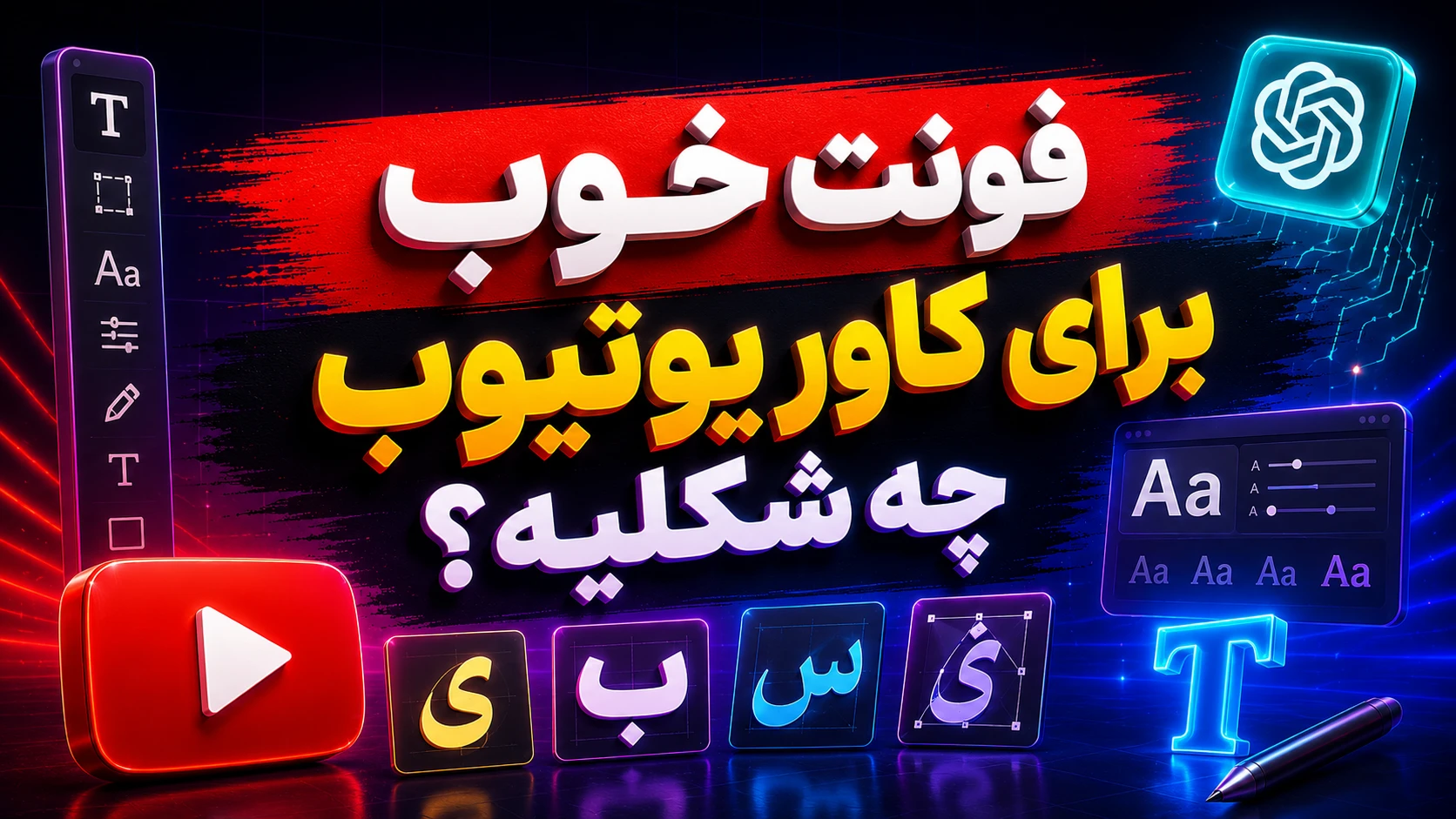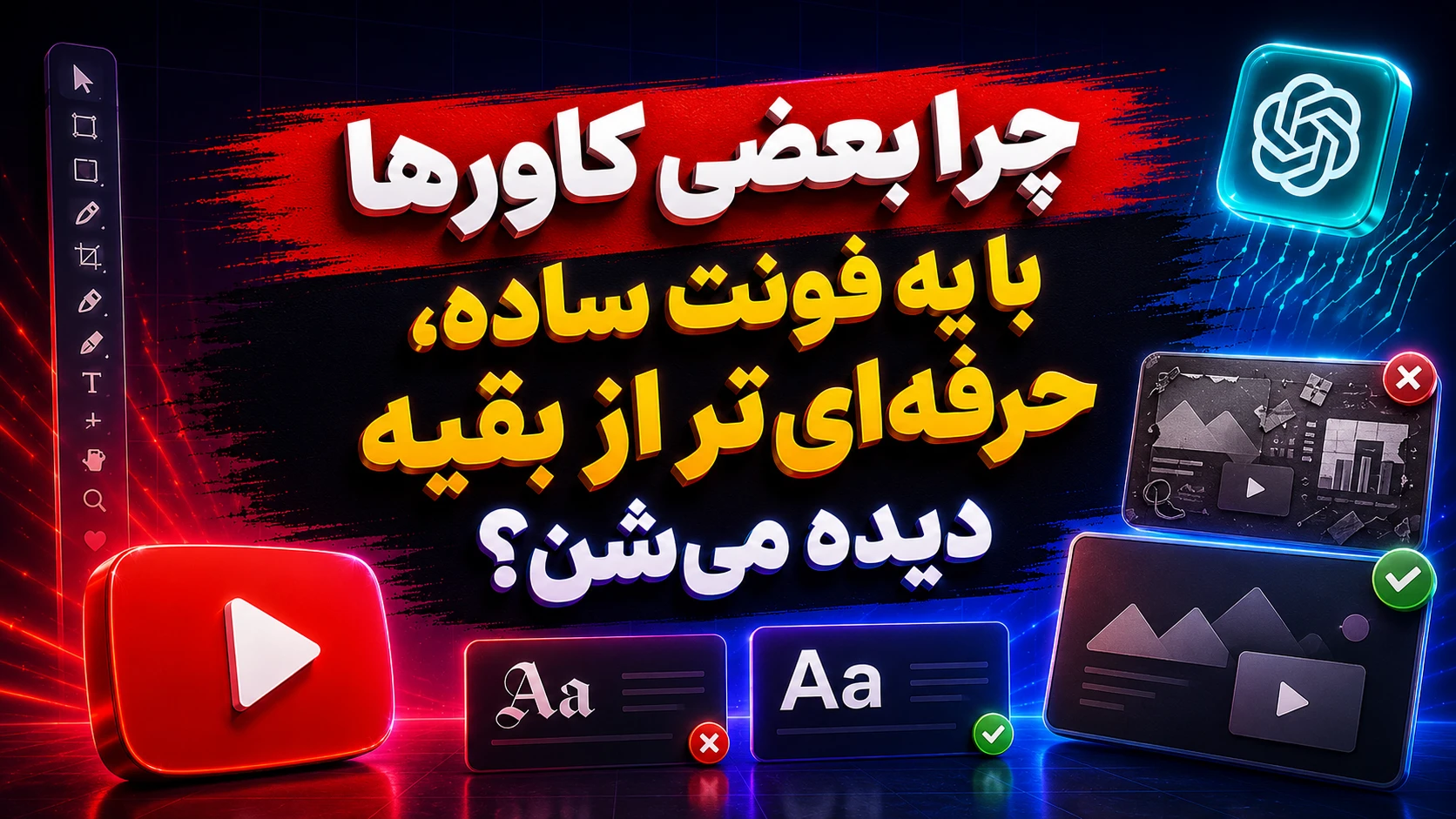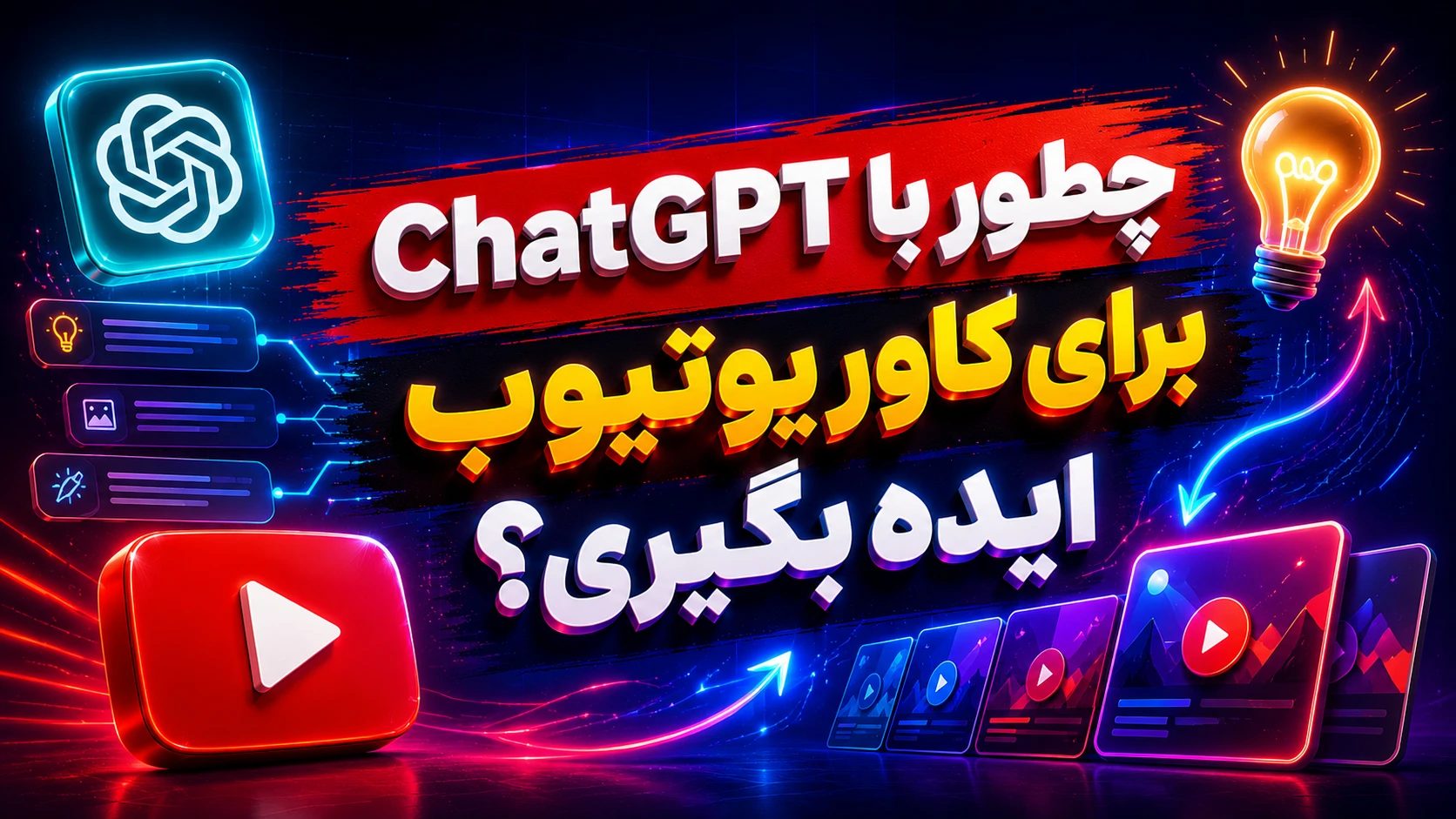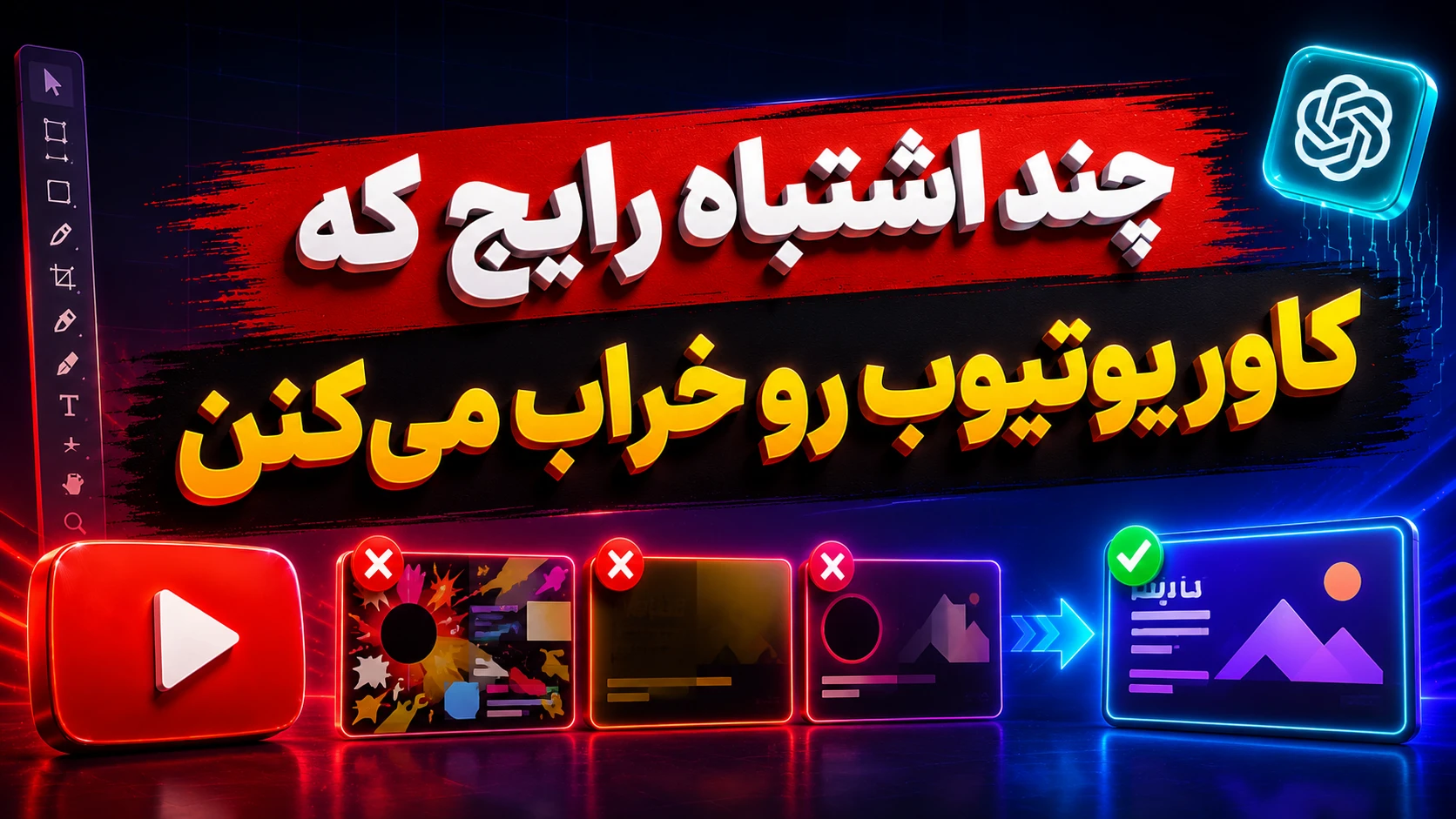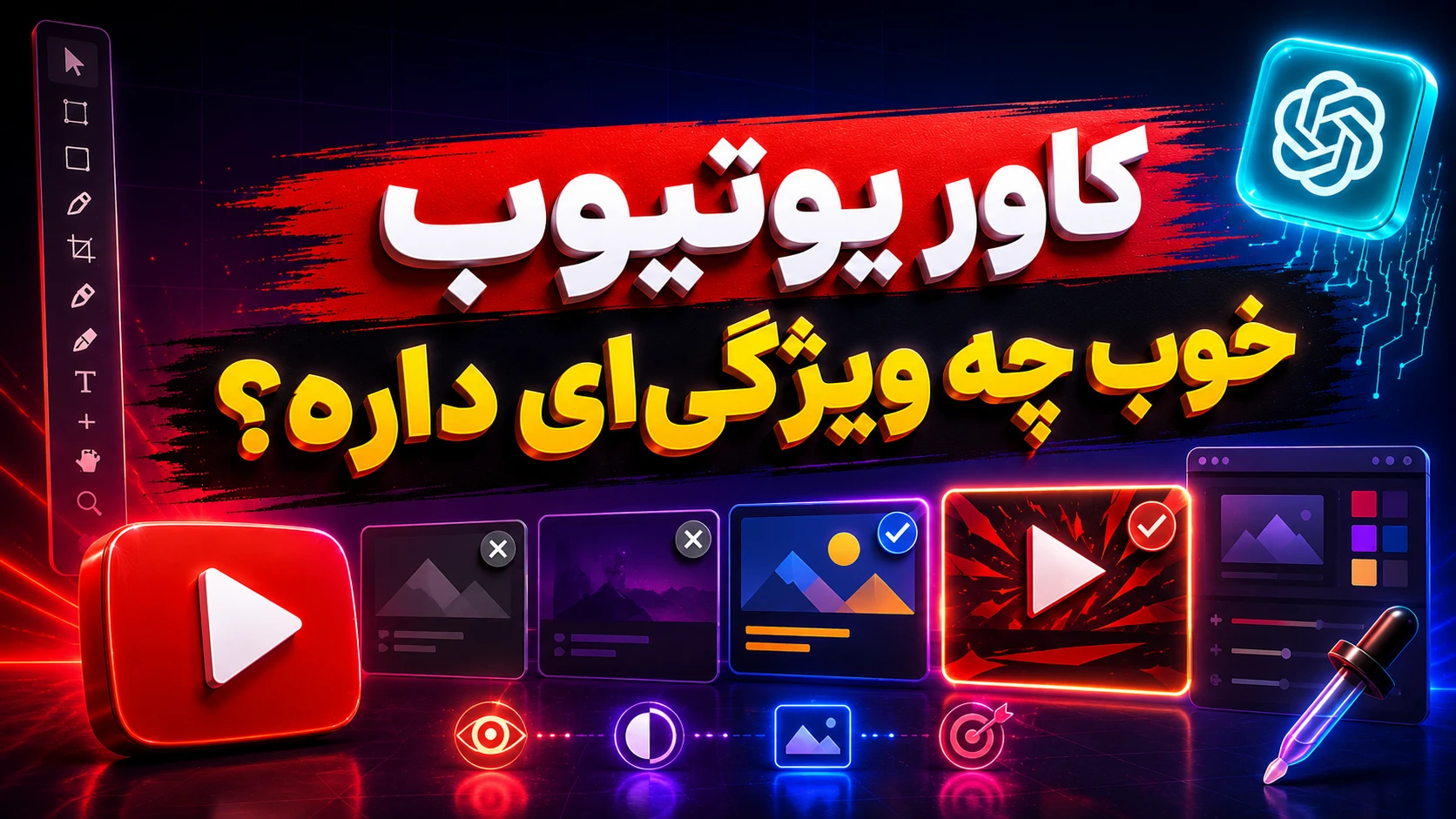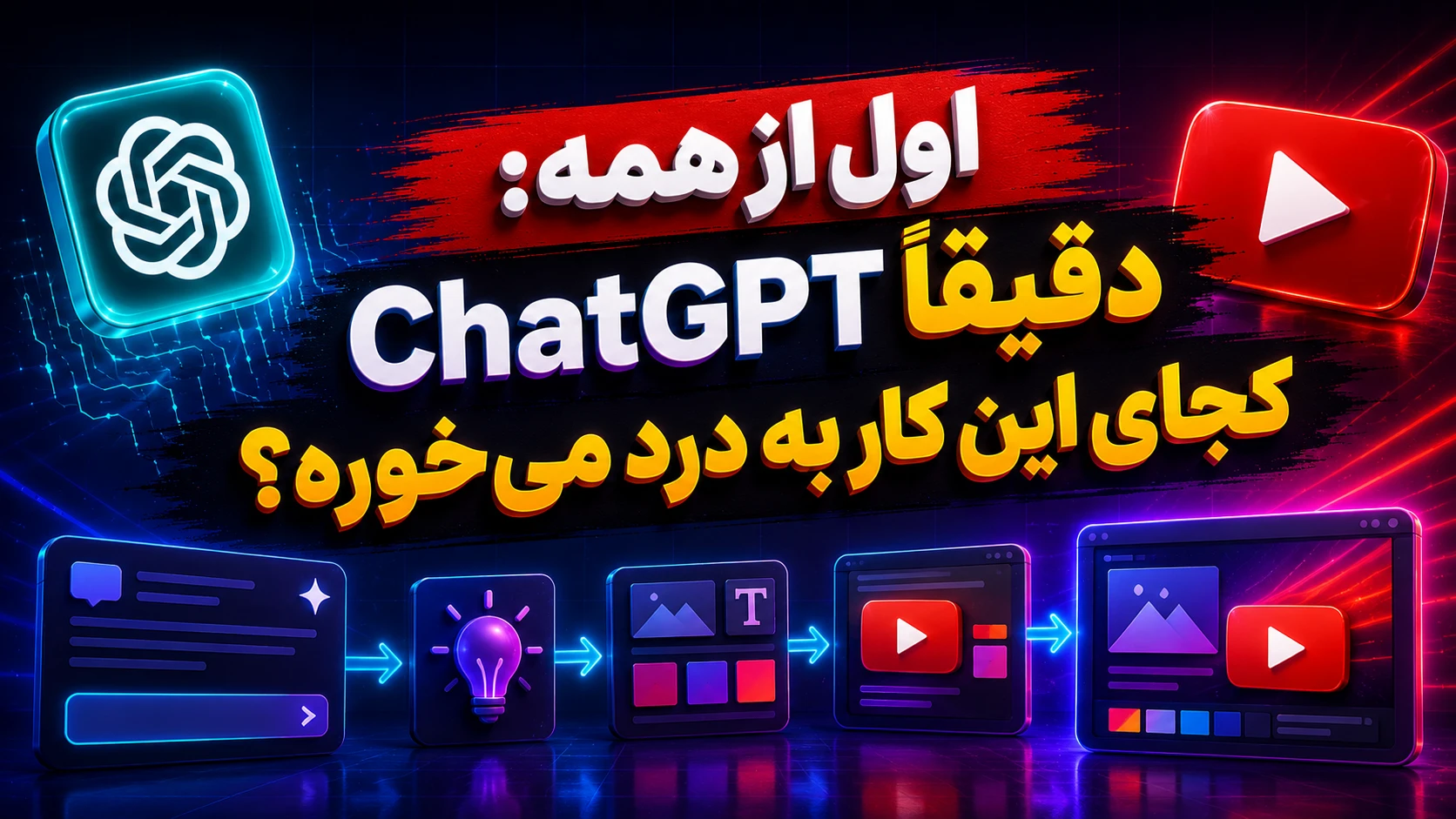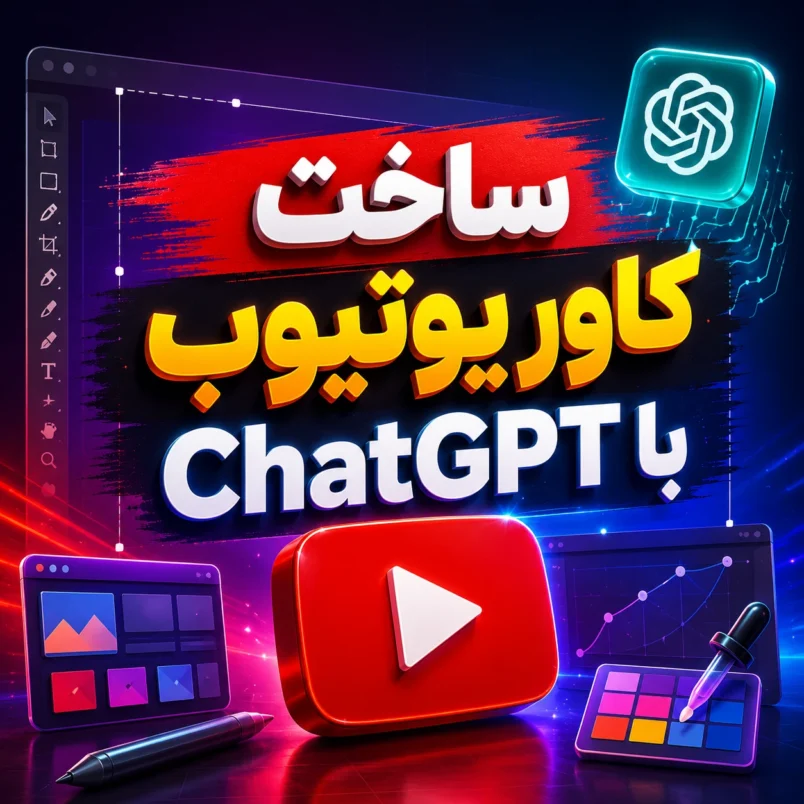
ساخت کاور یوتیوب با ChatGPT؛ این فونت‌ها ویدئوت رو نجات می‌دن!
ساخت کاور یوتیوب با ChatGPT
اگر بخوام خیلی ساده بگم، کاور یوتیوب همون چیزیه که یا کاربر رو نگه می‌داره، یا باعث می‌شه از کنارش رد بشه. یعنی قبل از اینکه خود ویدئو دیده بشه، قبل از اینکه عنوان باز بشه، قبل از اینکه کسی بفهمه اصلاً تو چی گفتی، کاور باید کار خودش رو بکنه. یوتیوب هم دقیقاً روی همین نقطه دست می‌ذاره؛ توی راهنمای رسمی خودش می‌گه بیننده‌ها معمولاً اول از همه thumbnail و title رو می‌بینن و همون‌ها بهشون کمک می‌کنن بفهمن ویدئو درباره چیه و تصمیم بگیرن که بازش کنن یا نه. یوتیوب همچنین پیشنهاد می‌کنه از تصویر شلوغ و پیچیده دوری کنی، متن اگر گذاشتی خوانا باشه، و thumbnail تا جای ممکن بزرگ طراحی بشه.
اول از همه: ChatGPT دقیقاً کجای این کار به درد می‌خوره؟
ChatGPT می‌تونه توی مرحله ایده‌پردازی، نوشتن تیتر، پیشنهاد دادن ساختار بصری، و حتی ساخت یا ویرایش تصویر بهت کمک کنه. OpenAI در راهنمای رسمی خودش گفته ChatGPT Images می‌تونه هم تصویر جدید بسازه و هم تصویر موجود رو ویرایش کنه. همچنین در راهنمای پرامپت‌نویسی رسمی OpenAI تأکید شده که هرچی دستور دقیق‌تر و روشن‌تر باشه، خروجی مفیدتر درمیاد.
یعنی لازم نیست از همون اول خودت همه‌چیز رو حدس بزنی. می‌تونی از ChatGPT بخوای برای یه ویدئوی آموزشی، تبلیغاتی یا خبری، چند ایده برای کاور بده، چند مدل تیتر پیشنهاد کنه، و حتی بگه متن کجا بشینه و بک‌گراند چه حال‌وهوایی داشته باشه. اینجوری قبل از ورود به فتوشاپ، مسیرت روشن‌تر می‌شه و کمتر وقتت هدر می‌ره.
کاور یوتیوب خوب چه ویژگی‌ای داره؟
کاور خوب، اول از همه باید سریع فهمیده بشه. نه لازم داره همه‌چیز رو توضیح بده، نه باید شلوغ و پر از جزئیات بی‌ربط باشه. یوتیوب هم توی راهنمای thumbnail می‌گه طراحی نباید زیادی پیچیده بشه، از rule of thirds می‌تونی استفاده کنی، و اگر متن می‌ذاری، فونت باید راحت خوانده بشه. همین راهنما تأکید می‌کنه که thumbnail باید تا حد ممکن بزرگ باشه چون روی دستگاه‌های مختلف متفاوت دیده می‌شه.
از اون طرف، یوتیوب برای thumbnail سفارشی هم اندازه پیشنهادی 1280×720 با نسبت 16:9 رو مطرح می‌کنه، و حداقل عرض 640 پیکسل رو قبول می‌کنه. پس اگر بخوای واقعاً کار تمیز دربیاد، از همون اول با همین منطق جلو برو.
حالا این استانداردها به ما چی می‌گن؟ خیلی ساده: کاور یوتیوب باید هم واضح باشه، هم درشت، هم کم‌حرف ولی اثرگذار. یعنی متن کوتاه، رنگ خوب، فونت درست، و فضایی که چشم رو خسته نکنه.
فونت خوب برای کاور یوتیوب چه شکلیه؟
فونت مناسب برای کاور یوتیوب باید چند تا کار رو هم‌زمان انجام بده. باید از دور بخونه، باید روی موبایل جواب بده، باید با موضوع ویدئو بخونه، و باید در کنار تصویر گم نشه. این همون جاییه که خیلی از طرح‌ها زمین می‌خورن، چون یا فونت زیادی فانتزیه یا زیادی نازکه یا با بک‌گراند دعوا می‌کنه.
برای کاور یوتیوب، معمولاً این مدل فونت‌ها بهتر جواب می‌دن:
• فونت‌های ضخیم و خوانا برای تیترهای کوتاه
• فونت‌های مدرن و تمیز برای ویدئوهای آموزشی
• فونت‌های جدی‌تر و شیک‌تر برای محتواهای حرفه‌ای
• فونت‌های کمی جسورتر برای موضوعات کلیک‌خور و زرد
از کجا بفهمیم چه فونتی به کارمون میاد؟
اینجا دو راه داری. راه اول اینه که از همون اول چند فونت مختلف تست کنی و ببینی کدومش روی کاور بهتر می‌شینه. راه دوم اینه که از طرح‌های آماده الهام بگیری و فونت‌های نزدیک به حس کار رو پیدا کنی. برای همین، مقاله ۵ سریع‌ترین روش برای تشخیص فونت از روی عکس خیلی به درد می‌خوره، چون کمک می‌کنه حس فونت رو بهتر بشناسی و برای کاور یوتیوب، دقیق‌تر انتخاب کنی.
یه نکته مهم هم اینه که اگر هنوز برای انتخاب فونت مرددی، یه نگاهی به بهترین فونت‌های رایگان برای طراحی با فتوشاپ + دانلود هم بندازی. اون مقاله می‌تونه بهت نشون بده کدوم جور فونت‌ها برای طراحی‌های درشت و خوانا بیشتر به کارت میاد.
چطور با ChatGPT برای کاور یوتیوب ایده بگیری؟
به‌جای اینکه مستقیم بری سراغ ساخت نهایی، اول از ChatGPT بخواه چند مسیر مختلف جلوت بذاره. مثلاً می‌تونی این پرامپت رو بدی:
برای یک کاور یوتیوب درباره آموزش فتوشاپ، ۵ ایده بصری بده.
لحن کاور: آموزشی، حرفه‌ای و کمی هیجان‌انگیز
رنگ‌های اصلی: بنفش، آبی و زرد
تیتر باید کوتاه و خیلی خوانا باشه
جای تیتر را در سمت چپ بگذار
بک‌گراند تمیز و ساده باشد
این مدل پرامپت باعث می‌شه ChatGPT فقط یه جواب خشک نده، بلکه چند ایده واقعی و قابل‌استفاده بهت بده. OpenAI هم در راهنمای پرامپت‌نویسی رسمی خودش می‌گه هرچی درخواستت روشن‌تر و دقیق‌تر باشه، نتیجه بهتر درمیاد.
اگر خواستی خود تصویر اولیه رو هم بسازی یا اصلاح کنی، ChatGPT این امکان رو هم داره که تصویر جدید بسازه یا روی تصویر موجود تغییر بده. این قابلیت برای وقتی خوبه که بخوای از ایده به خروجی برسی، بدون اینکه از صفر همه‌چیز رو دستی بکشی.